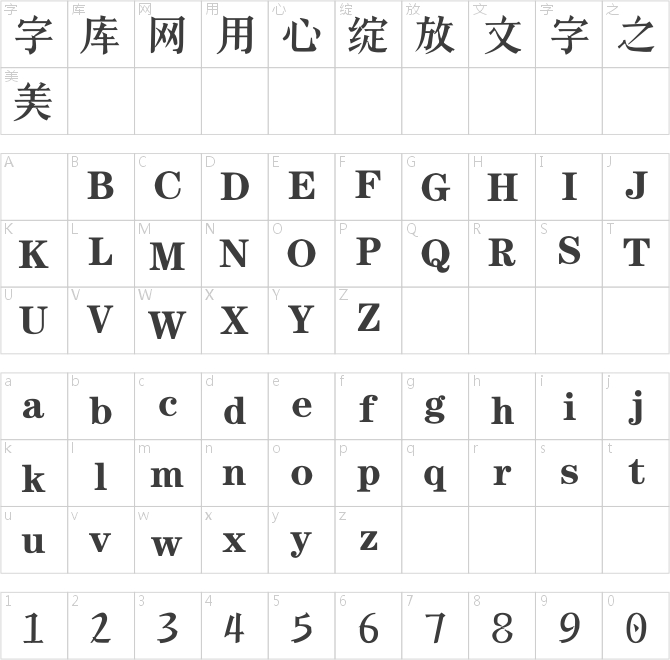
字體名稱: 逐浪海棠居刻本
逐浪海棠居刻本字
海棠居刻本字,
由逐浪字庫團(tuán)隊,歷時兩年研發(fā),
基于2020年3月發(fā)布的unicode13標(biāo)準(zhǔn)構(gòu)建,以gb2312為規(guī)范,支持全語言擴(kuò)展,支持webfont渲染,支持color采色渲染,
件專注漢語基礎(chǔ)數(shù)據(jù)元研究與文明基石拓荒者。
逐浪海棠居刻本字字體海棠居刻本字庫是一款讓人賞心悅目、百看不厭的中文字體,適合各類廣告和產(chǎn)品包裝設(shè)計應(yīng)用,字體大小4.05MB,格式為otf字體,上傳用戶是曾紹文,作者/版權(quán)方為逐浪字庫